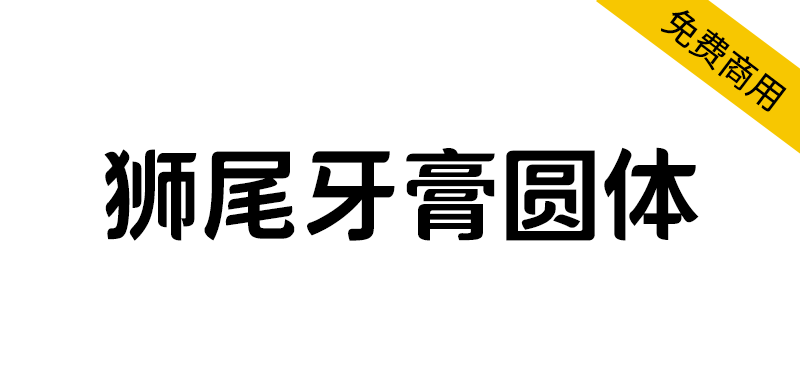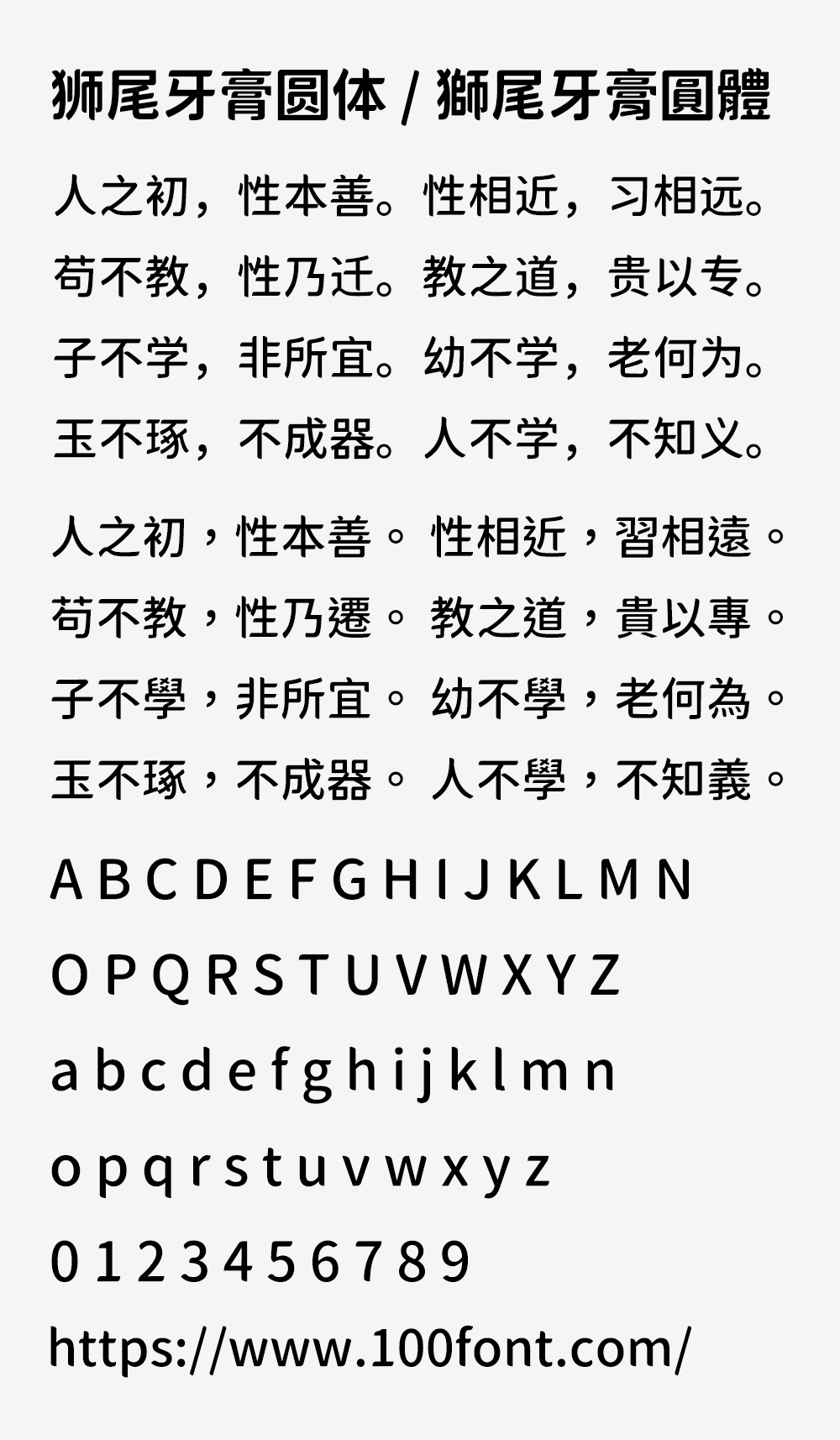
狮尾牙膏圆体基于思源黑体的变圆和拔脚改造,更加简明现代化的字体。狮尾牙膏圆体的特色是「口」字的左上和右下是圆体,外型像挤出来的牙膏。和思源黑体一样,有7种字重,支持简体中文、繁体中文、韩文与日文,可以免费商用,欢迎大家自由应用、自由优化、自由改作!
狮尾牙膏圆体和狮尾半月长像几乎一样。差别在「中」字中间的口,半月会变圆,牙膏是左上和右下是圆。单独遇到「口」部件时,2个字体有时是一样,有时方向会相反,狮尾牙膏圆体套用的规则比较明确。